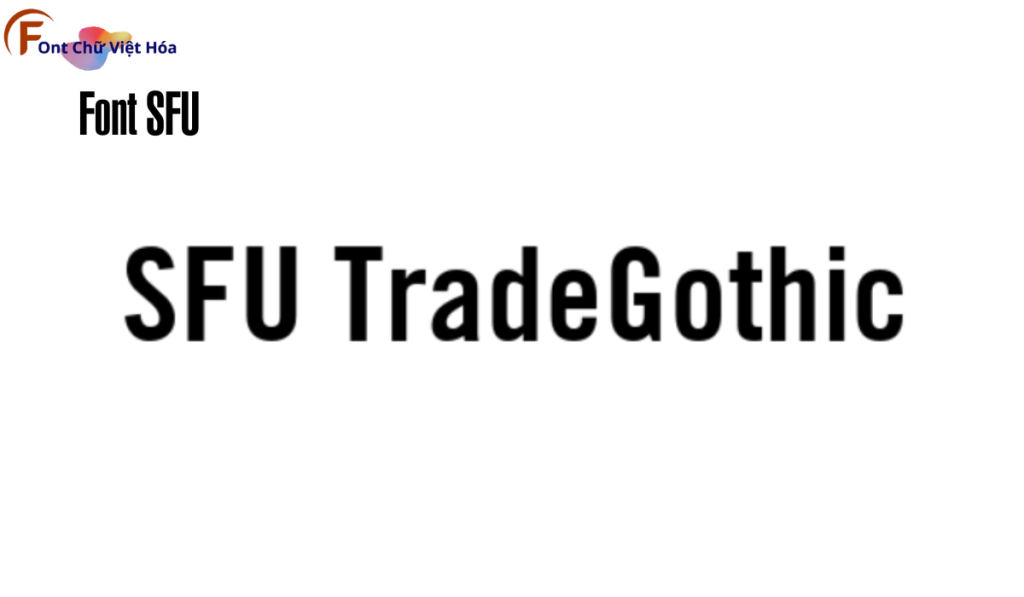
Font SFU Tradegothic Việt Hóa
Tác giả: SFU
Bộ Font: SFU
Phân loại: Cổ điển
Độ dày: Light, Regular, Bold
Font SFU Tradegothic Việt Hóa là một font chữ độc đáo, mang phong cách sans-serif hiện đại với các đường nét mạnh mẽ và cá tính, thuộc bộ font SFU. Thiết kế của SFU Tradegothic tập trung vào sự rõ ràng và dễ đọc, đặc biệt phù hợp cho các thiết kế đòi hỏi tính thẩm mỹ cao như poster, logo, và tiêu đề. Với tỷ lệ chữ cân đối và các đường nét đậm, font này tạo ra ấn tượng thị giác mạnh mẽ và giúp tối ưu hóa không gian trong thiết kế. Font này cũng đã được Việt hóa, mang đến sự linh hoạt và tiện dụng cho các dự án thiết kế bằng tiếng Việt.